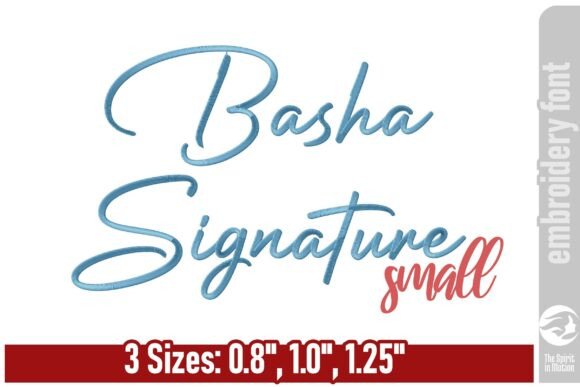
Basha Signature Font - Small
Mencari elemen reka bentuk yang sesuai boleh menjadi mencabar, tetapi Basha Signature Font - Small menawarkan koleksi luar biasa yang menaik taraf karya anda serta-merta.
Dicipta dengan ketepatan, Basha Signature Font - Small menyediakan vektor yang bersih, tipografi yang licin dan lesen komersial untuk ketenangan fikiran.
Sama ada anda mencipta produk POD (Print on Demand), jemputan perkahwinan atau grafik media sosial, Basha Signature Font - Small amat bersesuaian.